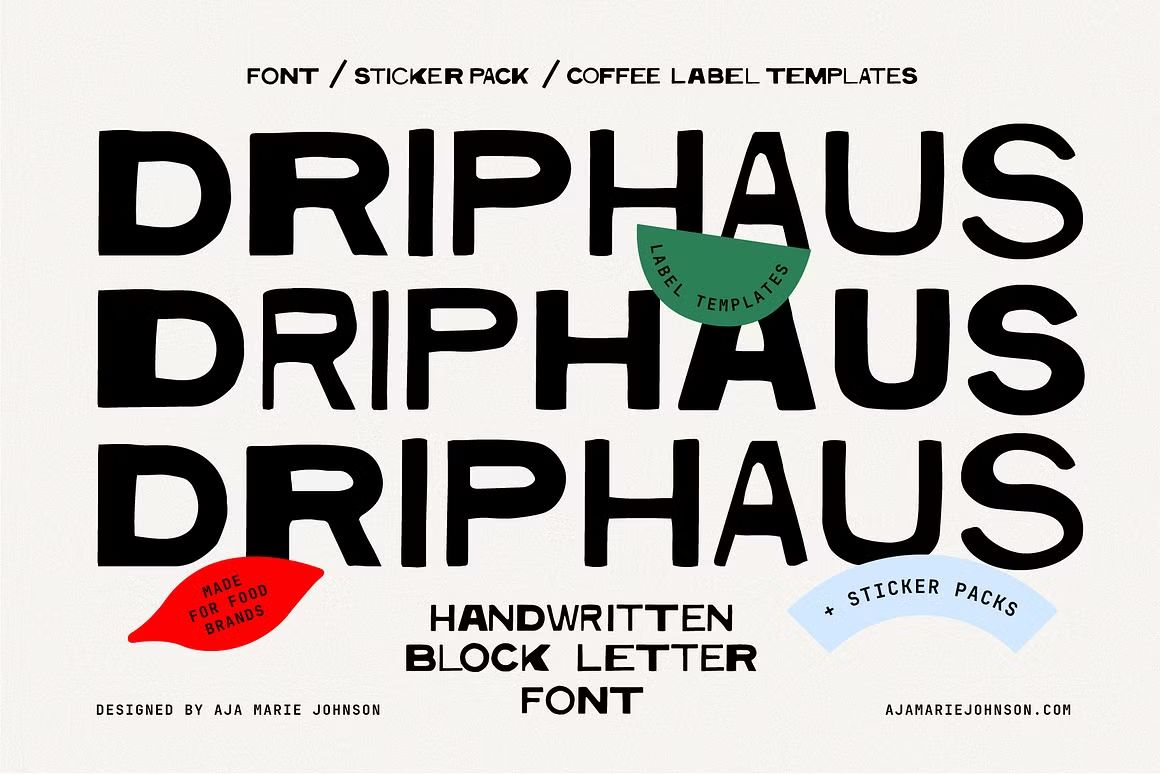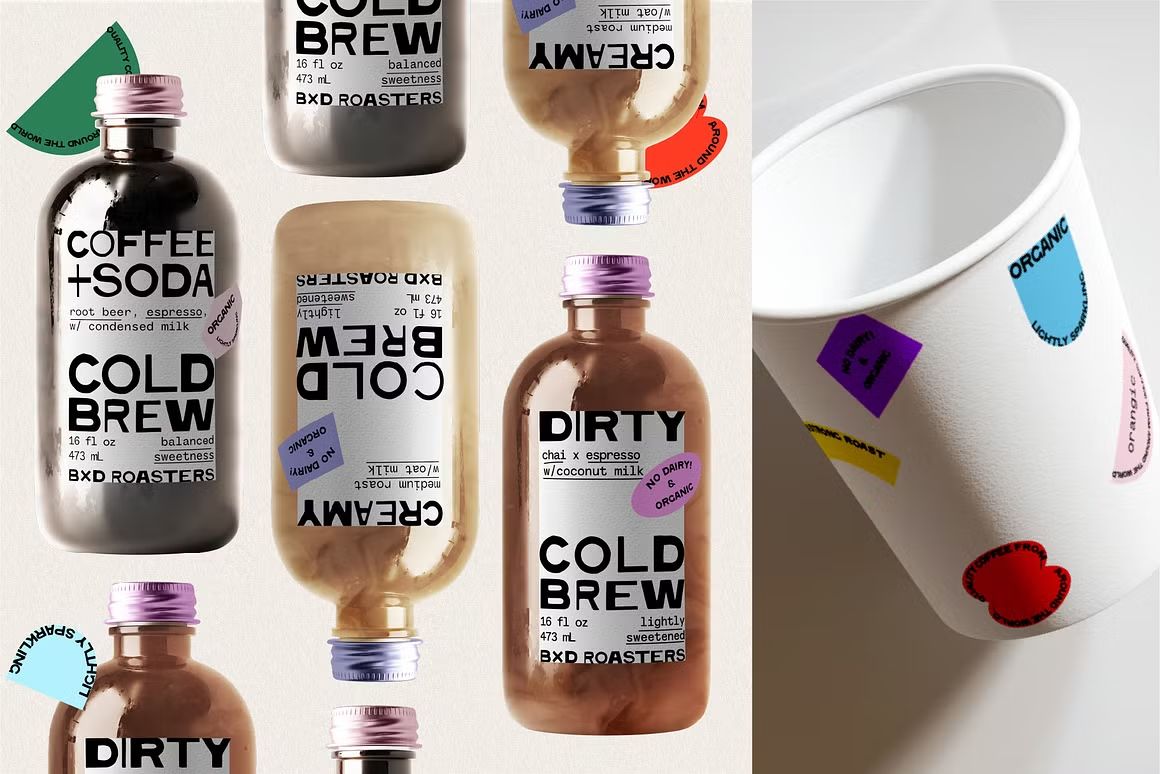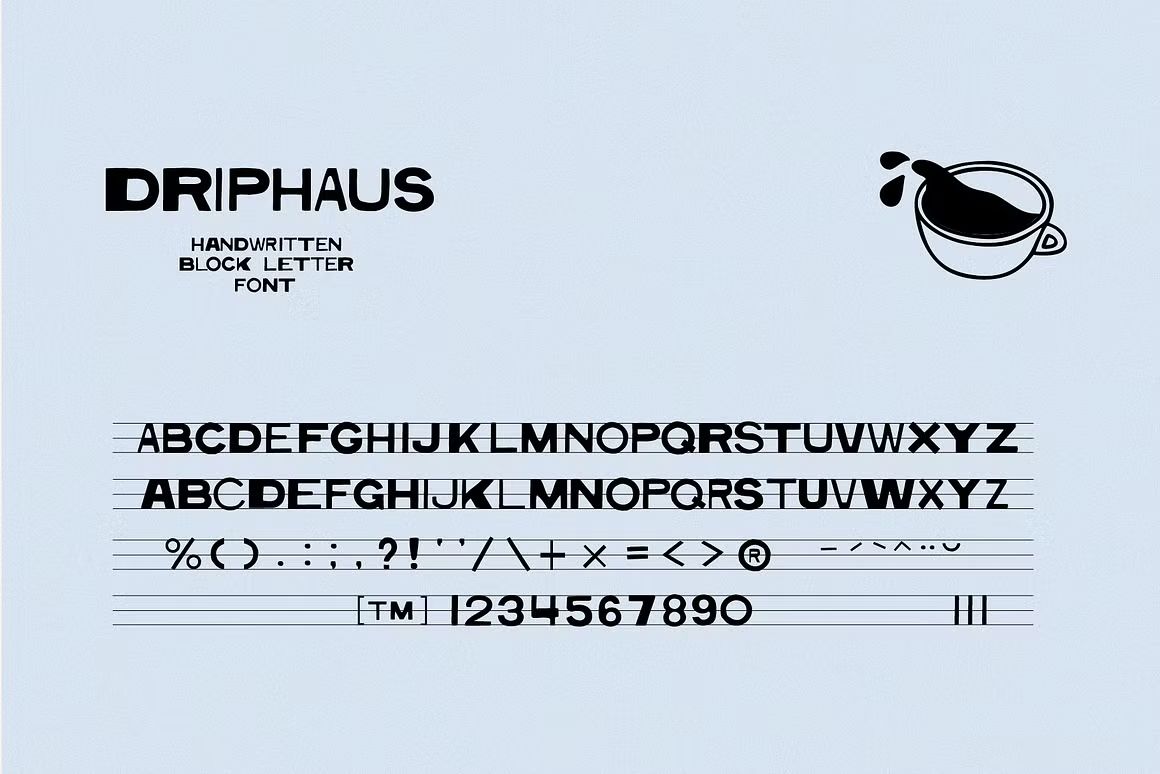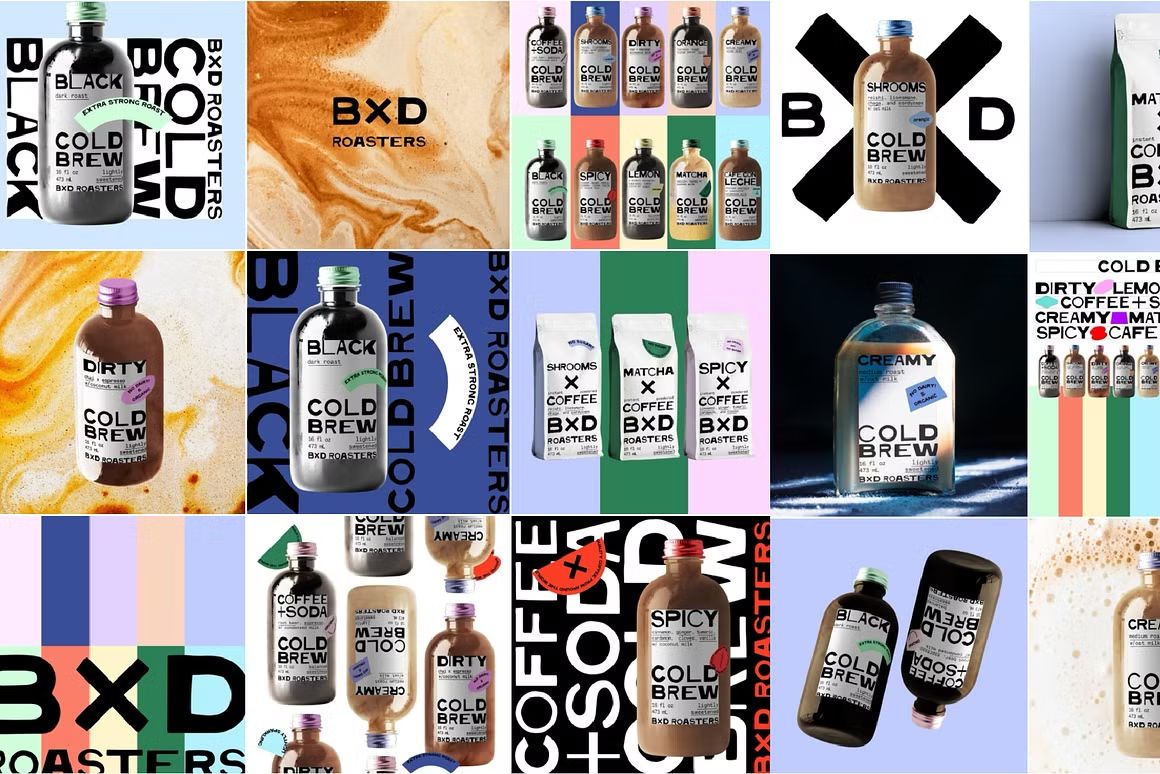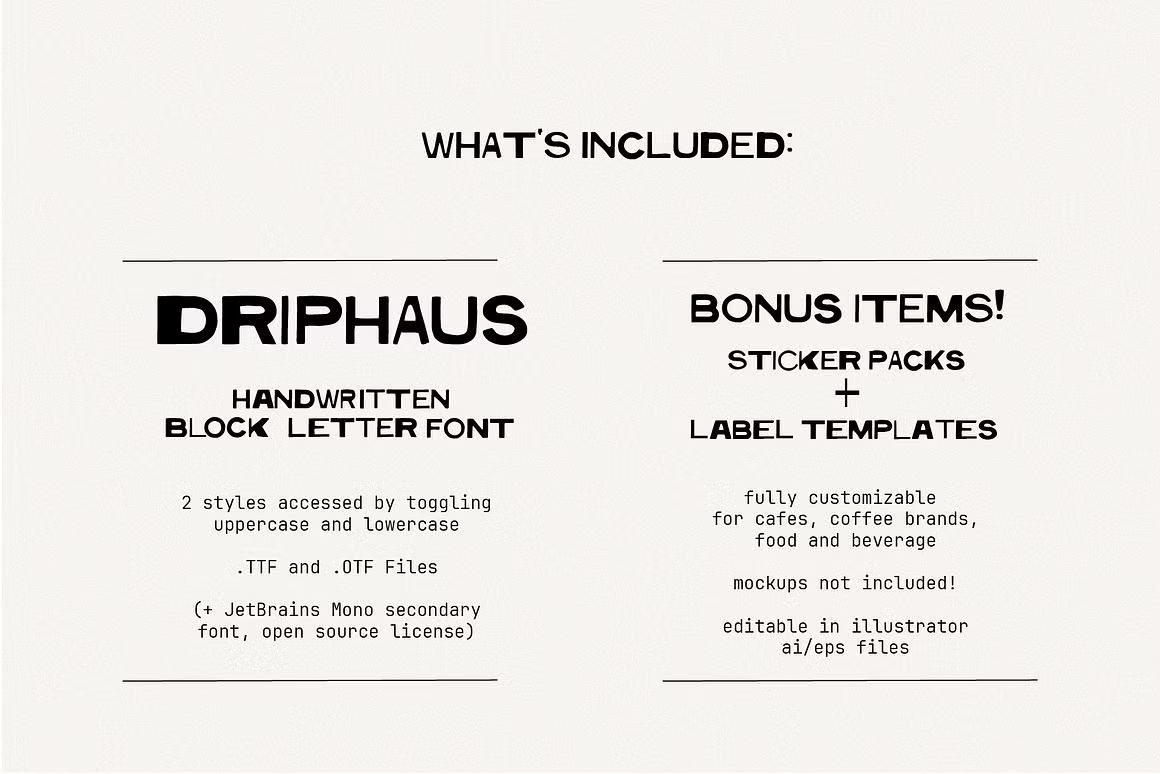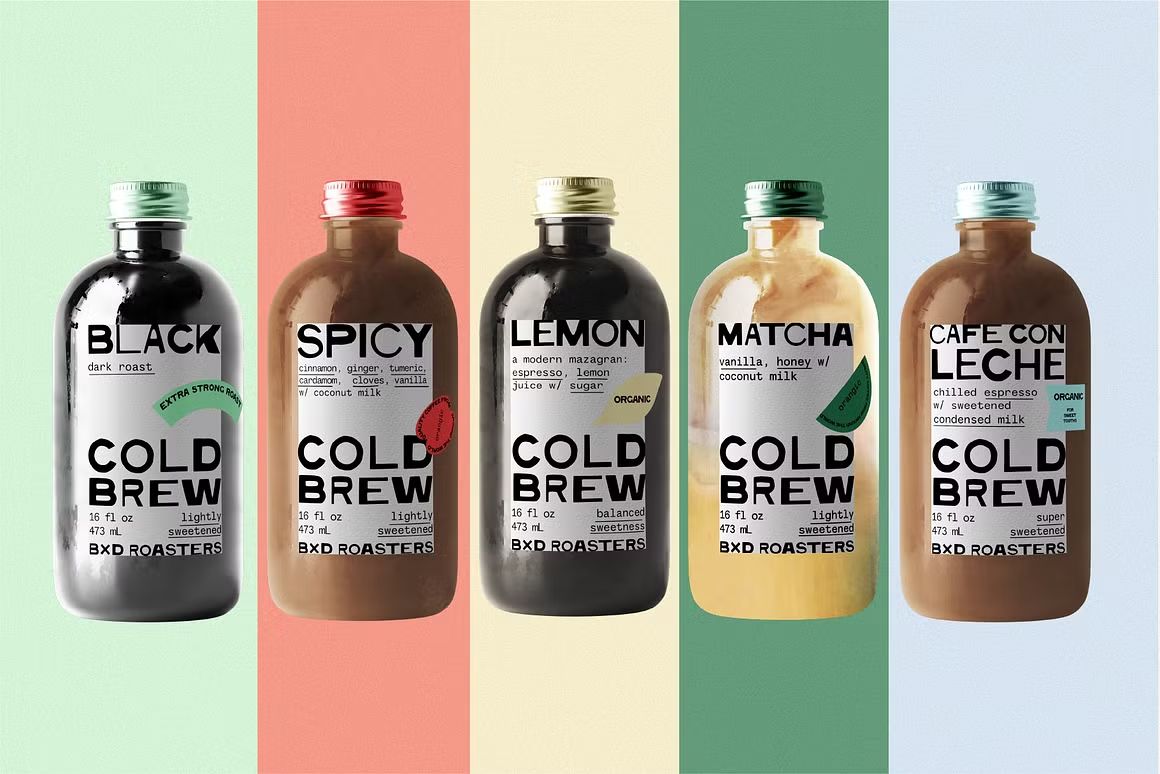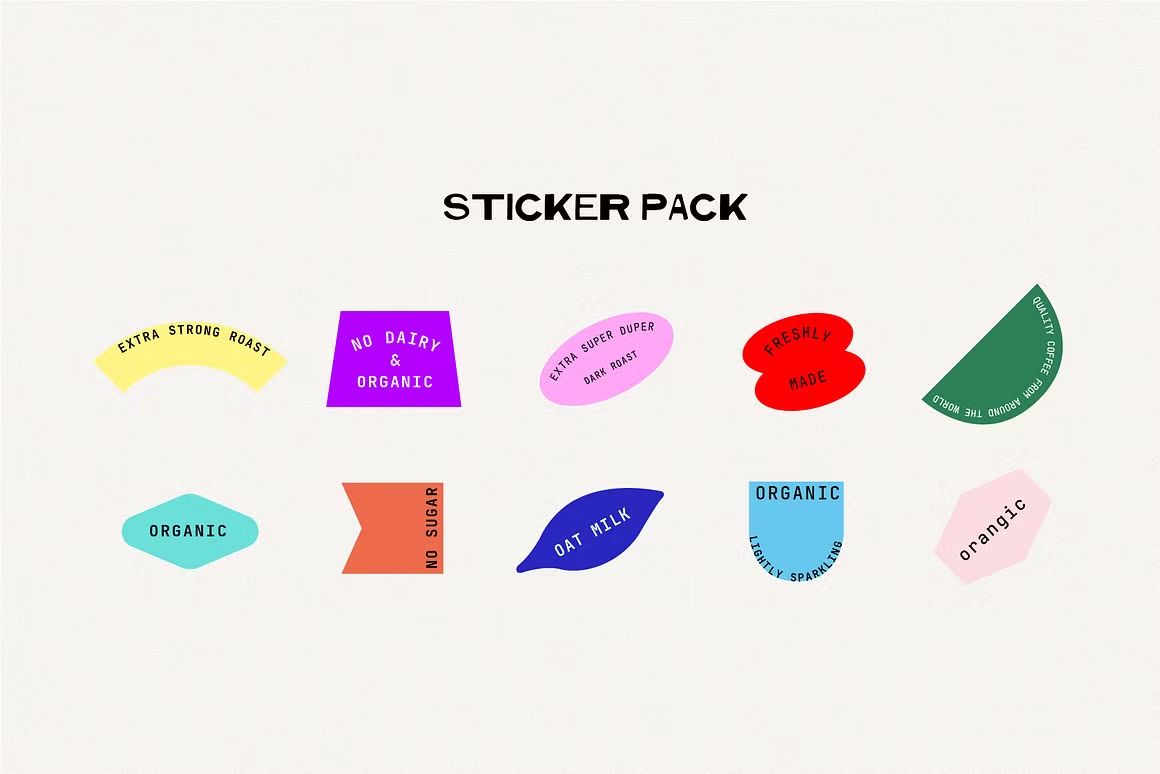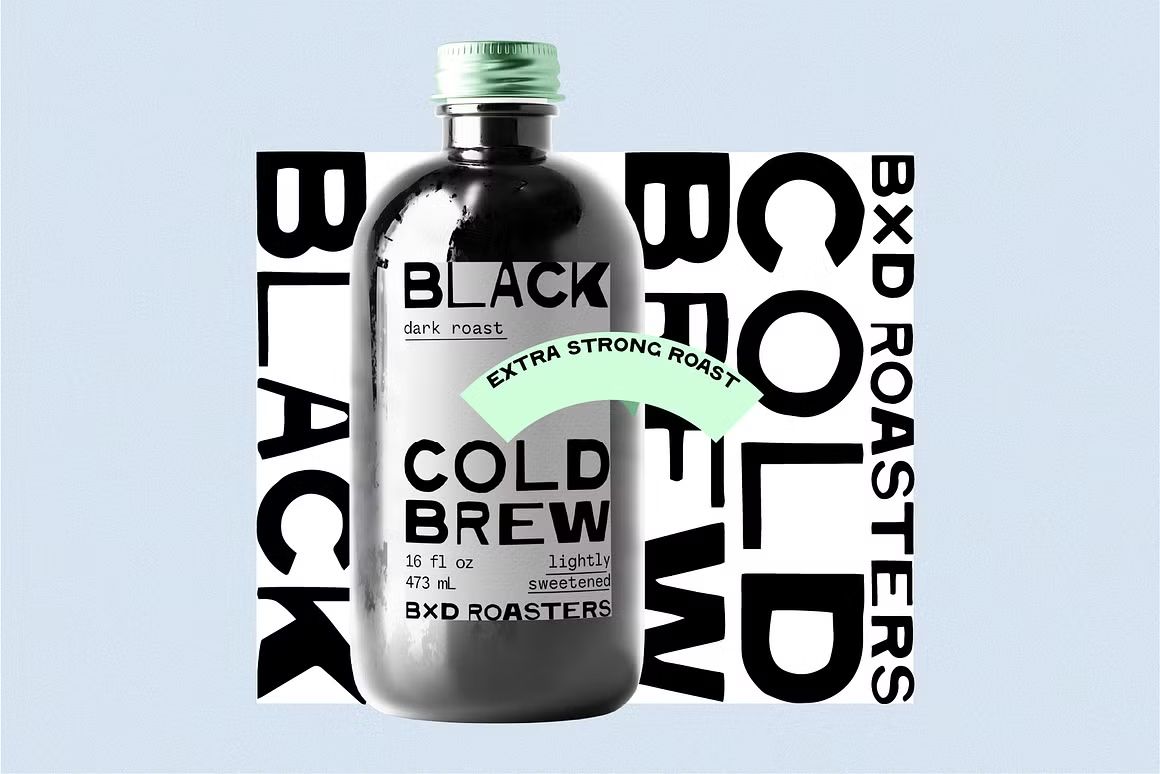
Driphaus – Handwritten Font
Driphaus adalah font handwritten bergaya kasual dan ramah, cocok untuk desain kreatif seperti quotes, logo, dan media sosial. Format OTF/TTF/WOFF, siap pakai di berbagai platform.
Driphaus adalah font handwritten yang bergaya kasual dan playful, dengan garis-garis halus dan bentuk huruf yang mengalir alami. Cocok untuk desain yang membutuhkan sentuhan personal dan ramah, seperti undangan, quotes, logo kreatif, kemasan, dan media sosial. Font ini memberikan kesan santai namun tetap rapi dan mudah dibaca, menjadikannya pilihan ideal untuk berbagai kebutuhan desain informal dan kreatif.
• Gaya tulisan tangan natural & kasual
• Cocok untuk logo, quotes, undangan, dan konten sosial
• Termasuk huruf besar, kecil, angka, dan simbol